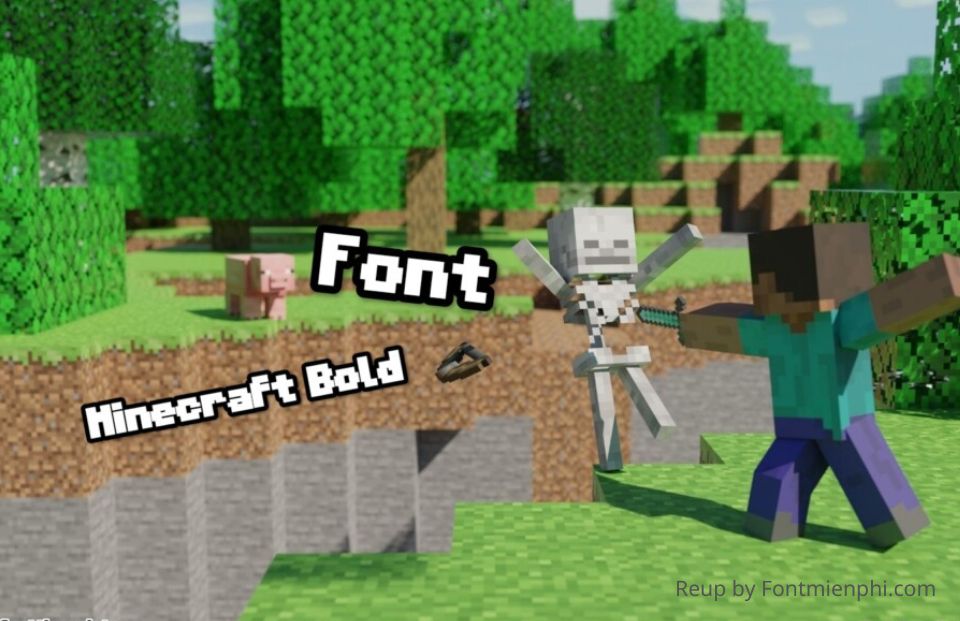
Bạn đang tìm kiếm một phông chữ mang phong cách pixel, 8-bit để thiết kế ảnh bìa, thumbnail YouTube hay làm overlay cho luồng stream của mình? Không cần tìm đâu xa, Font Minecraft Bold Việt Hóa chính là mảnh ghép còn thiếu cho các thiết kế của bạn!
🌟 Tại sao bạn nên tải ngay Font Minecraft Bold?
Nếu là một fan cứng của tựa game sinh tồn đình đám Minecraft, chắc chắn bạn không còn xa lạ gì với kiểu chữ khối vuông vức đặc trưng. Phiên bản Minecraft Bold Việt Hóa mang đến những ưu điểm tuyệt vời:
Đậm chất Retro & Gaming: Nét chữ dày, to bản và được cấu tạo từ các “pixel” tạo hiệu ứng thị giác mạnh mẽ, ngay lập tức thu hút sự chú ý của người xem.
Hỗ trợ Tiếng Việt 100%: Tạm biệt nỗi ám ảnh “lỗi font”, “lệch dấu” khi gõ tiếng Việt. Bản việt hóa đã được tinh chỉnh kỹ lưỡng từng dấu câu, giúp bạn thoải mái sáng tạo nội dung.
Hiệu quả hiển thị cao: Nhờ đặc tính in đậm (Bold), font chữ này cực kỳ phù hợp để làm Tiêu đề (Title), giữ được sự rõ ràng ngay cả khi đặt trên các nền ảnh nhiều chi tiết hoặc bị thu nhỏ trên màn hình điện thoại.
💡 Mẹo thiết kế: Để dòng chữ trông giống y hệt như đang ở trong thế giới Minecraft, hãy kết hợp font này với màu xám nhạt/trắng, thêm hiệu ứng Drop Shadow (đổ bóng màu đen, không làm mờ viền) hoặc Stroke (viền chữ đen) nhé!